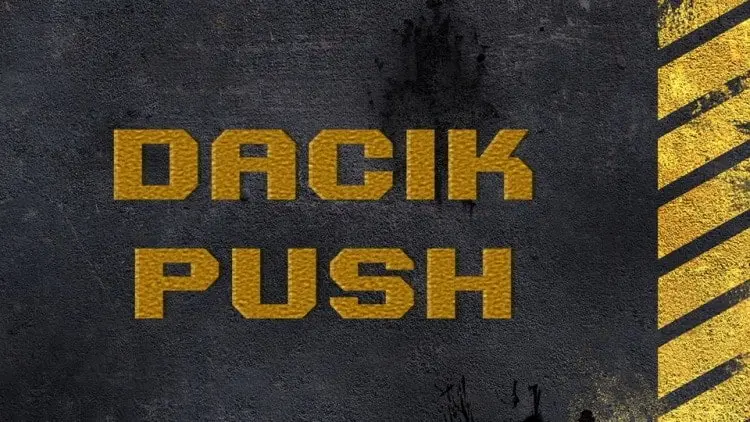
A fonte Dacik Push Display é uma escolha perfeita para quem procura destaque em designs visuais impactantes. Com suas linhas fortes e ângulares, essa fonte de designer Maxi Raikov traz a essência da letra do tipo sem serif. Seu formato robusto e as linhas diretas criam um poderoso contraponto aos outros elementos design, deixando sua marca mais marcante no meio de uma multidão. Além disso, Dacik Push oferece suporte multilíngue incluindo o inglês e o russo. Suas características elegantes e atraentes dão ao seu design um toque poderoso e imponente que se torna irresistível. Essa é uma fonte de destaque para designers em busca de criar algo realmente único e impactante, seja em logotipos, materiais publicitários ou qualquer outro tipo de design gráfico que exija destaque.